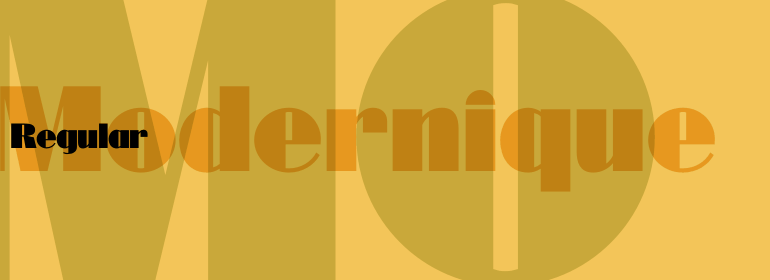
Modernique
Modernique,这款字体结构工整、笔画清晰,兼顾美观与易读性,适用于标题、正文、海报、包装、LOGO 等多种场景。字形优雅稳定,风格百搭耐看,适配日常排版与创意设计,让文字呈现更舒适、更具质感。Modernique一笔一画,皆是细节,以均衡的比例、流畅的线条打造舒适视觉体验,字形端正大气,风格简约现代。无论是商业设计、品牌宣传还是日常排版,都能轻松驾驭,让文字更有格调与力量。Modernique字体下载。